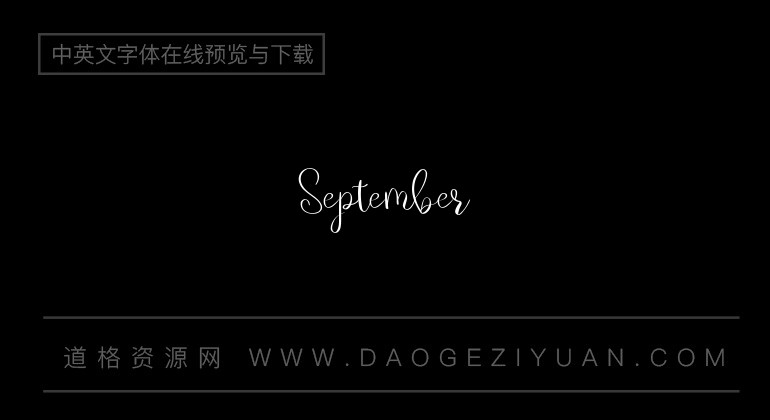
September 是一款极简、精致的英文字体,它由丹麦设计师 Martin Venezky 于2019年设计。September 字体以简洁的线条和精致的曲线结合,形成了简约而优雅的外观,是一款适用于日常文字排版的经典字体。September 字体的特点是,它的字体结构紧凑,拥有更多的变体,使其具有更好的适应性,同时也具有更强的视觉效果。September 字体还具有更强的可读性,可以有效地帮助读者更好地理解文字。内容介绍
September是一款非常不错的手写艺术字体,具有很好的视觉感,适合于文化类的宣传设计、商业类品牌的广告和产品包装设计以及个性化文字排版等较多场景。